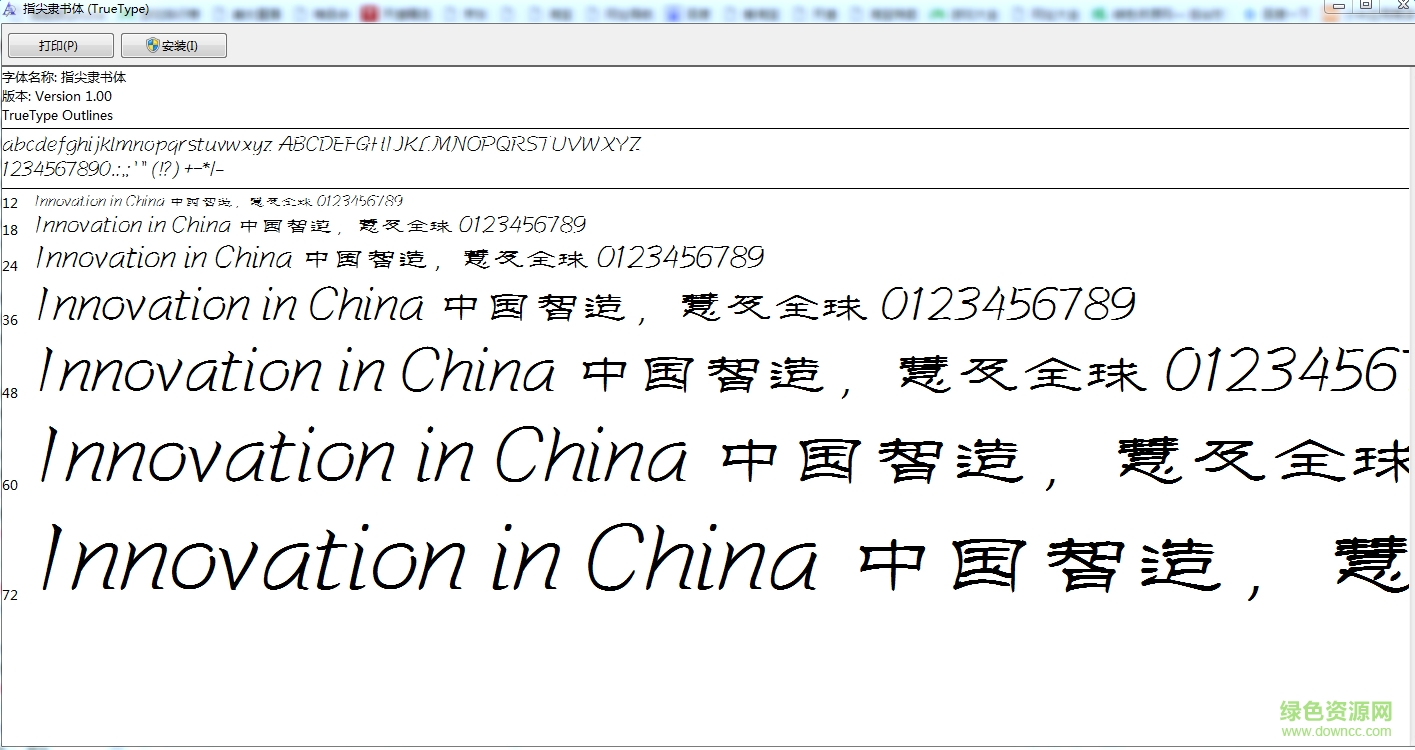
指尖隸書體是一款常常用于藝術(shù)設(shè)計方面的電腦字體,使用簡單,字形周正,骨骼清秀,看上去優(yōu)雅從容,喜歡的朋友歡迎在綠色資源網(wǎng)下載!
一款以隸書為原型所設(shè)計的藝術(shù)體字體帶給大家,指尖隸書體字體字形細(xì)致富有藝術(shù)性,非常的獨特漂亮,常適合廣告設(shè)計、平面設(shè)計、印刷包裝、正文標(biāo)題等人員使用。